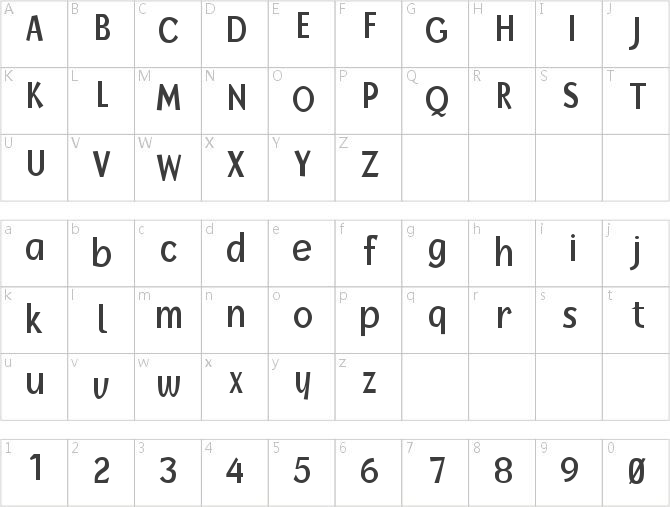
FZ BASIC 14 COND 詳情頁(yè)
FZ BASIC 14 COND字體字庫(kù)是一款讓人賞心悅目、百看不厭的英文字體,適合各類廣告和產(chǎn)品包裝設(shè)計(jì)應(yīng)用,字體大小0.04MB,格式為ttf字體,上傳用戶是Apple,作者/版權(quán)方為未知